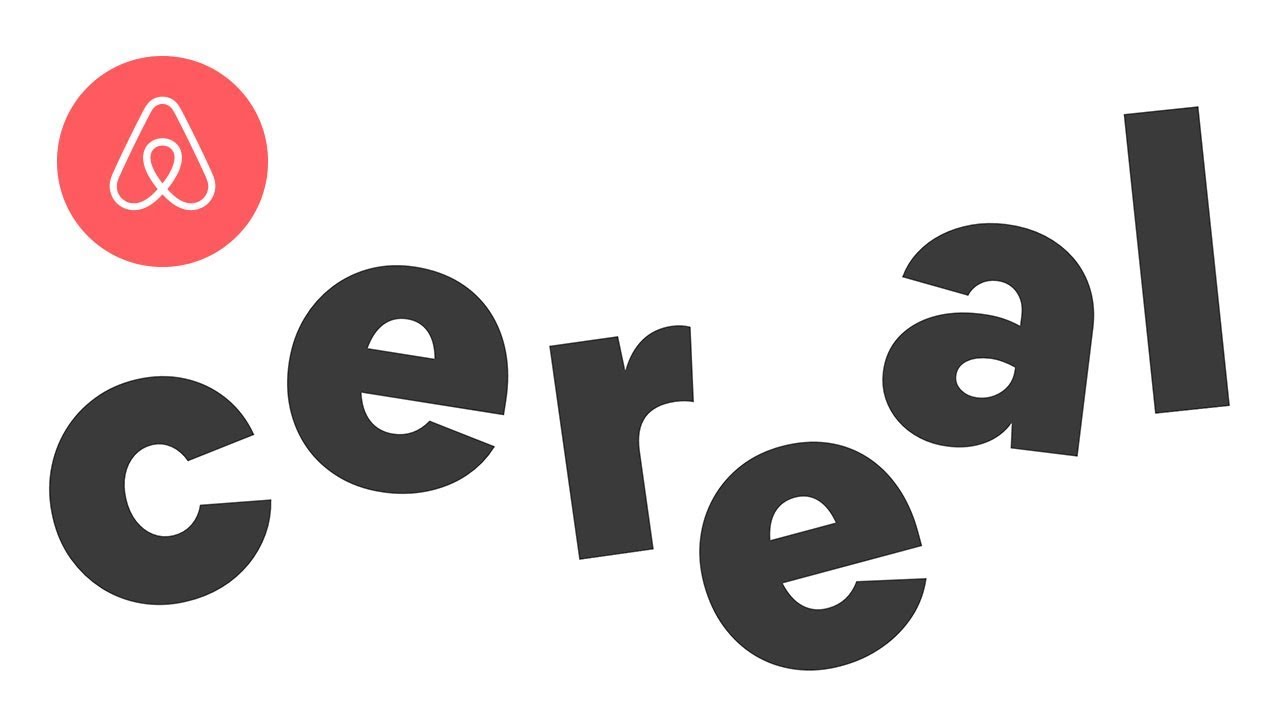
Airbnbが新しいフォント「Airbnb Cereal」を発表
現地の人から家を借りることができる民泊サービス「Airbnb」が、オンライン・オフラインの両方で自社のサービスを支えることが可能な書体「Airbnb Cereal」を発表しました。
Airbnb Cerealは国際的なフォントデザイン事務所のDalton Maagと共に作成された書体。どんなデザインに仕上がっているのかは以下のムービーを見ればわかります。
Airbnb Cerealを作成した経緯について、Airbnbのドレーク・チャン氏は「我々の仕事は極めて活版印刷と関わりが深いものです。『Airbnbmag(Airbnbによる雑誌)』や地下鉄の広告など、さまざまなものを通して人々にAirbnbというブランドを周知しようとしています。そんな中で、我々は提供するブランドを区別し、読みやすさやスケーラビリティ、特定のビジネスニーズにまで対応し、ブランドの個性を反映し、さらにオンラインとオフラインの両方で美しく機能する書体を求めていました」と語っています。
Airbnbではシステムフォントなどを参考にさまざまなフォントを分析したそうですが、「印刷に適していてもUIでの利用には適していない」など、オンラインでの利用とオフラインでの利用の両方でAirbnbの基準を満たすものを見つけることはできなかったそうです。そこで、著名なフォントデザイン事務所のDalton Maagと共にAirbnb Cerealを作成することとなった模様。
Airbnbの書体はウェブサイト上のボタンから現実世界に設置される巨大看板に至るまで、あらゆる場所で美しくある必要があるため、開発には多分野のチームの協力が必要だったそうです。チャン氏はデザイナー・フォトグラファー・映像制作者・作家・プロデューサーといったさまざまな分野に携わる人々で構成されたブランドマーケティングチームに所属していたため、Airbnbが社内で制作するさまざまなコンテンツとそのフォーマットにわたって、開発中のAirbnb Cerealをテストすることができたと語っています。
書体・スタイル・カラーパレットなど、Airbnbのデザインガイドラインの制作を担当する設計システムチームは、「その後の製品設計」について考えながらAirbnb Cereal制作プロジェクトに携わっていたそうです。設計システムチームは書体の読みやすさ・重み・質感・全体的な美しさ、という4つに焦点を当てており、製品デザイナーやアクセシビリティチームなどからのフィードバックを収集し、開発をサポートしたそうです。
Airbnb Cerealではフォントを読みやすくするために、さまざまな工夫を凝らしています。例えば、類似した見た目の文字や、別のフォントの類似した見た目の文字との区別がはっきりとつくように、フォントの開口部を大きめにとっています。また、読みやすさを向上させるため、小文字は全体的に背の高いデザインにしているとのこと。
UIデザインにおいて文字はかなり小さく使用されることがあり、使用するフォントによっては完全に消えてしまうこともあります。そこで、Airbnb Cerealは軽すぎず重すぎない絶妙のバランスを目指してデザインが行われたそうです。Airbnbのウェブサイト上ではAirbnb Cerealが読みやすい太さ・大きさで使用されており……
「Live There」と書かれた看板広告では、太めの重みのあるフォントとして利用されています。どちらもAirbnb Cerealで、まさにオンラインとオフラインの両方で活躍できる書体になったことがよくわかる一例となっています。
なお、Airbnb Cerealは非ラテン系の7つの言語をサポートしており、今後はさらなる言語のサポートを目指しているそうです。